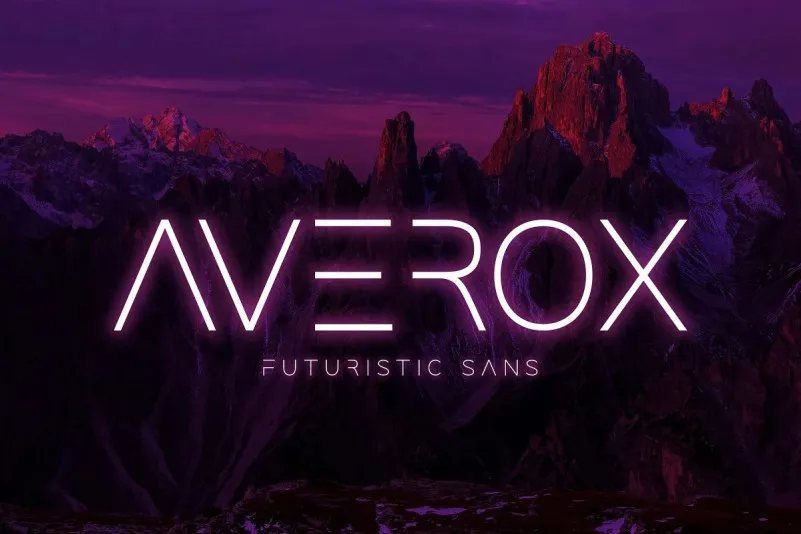
Averox é uma fonte display criada pela Almarkha Type inspirada no logotipo minimalista famoso, oferecendo um toque moderno e tecnológico para os projetos de design digital. Com seus traços clean e direto, Averox se destaca em qualquer layout de template, brochura ou vídeo publicitário. Perfeita para a criação de logotipos e marcas de marca, esta fonte é uma escolha ideal para quem procura algo que dê um toque único aos projetos digitais. Seja na web ou impressa em papel, Averox traz uma dose adicional de originalidade e modernidade a qualquer projeto visual. Este design criado pela 99designs, oferece tanto designers profissionais quanto iniciantes uma ferramenta poderosa para expressar suas ideias de forma única e inovadora.